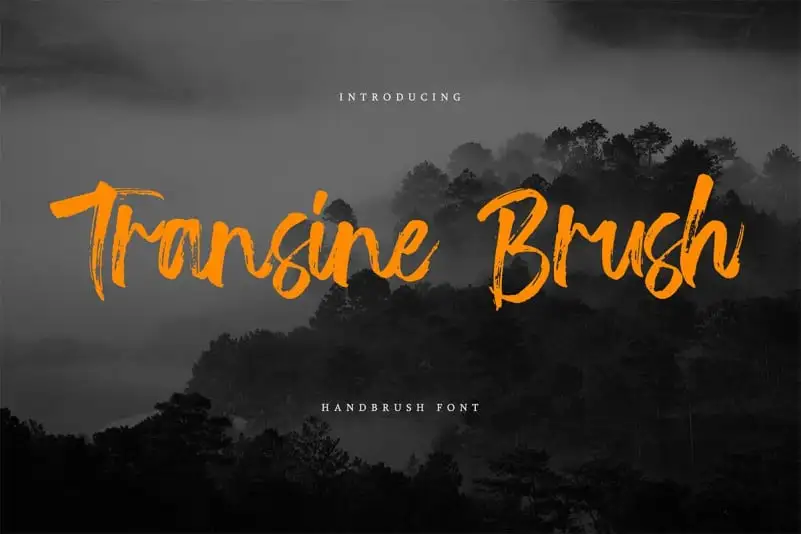
Transine Brush Font – Download Grátis
Introduzimos Transine Brush Font, uma elegante e moderna fonte feita com estilo casual. Criada pelo designer Vztype, Transine é perfeita para sua próxima criação visual como logotipos, cartões de presentes ou convites, caixas de embalagem, cabeçalhos, tipos de letra, letras finais, panfletos e até mesmo desenhos de roupas. Ideal tanto para projetos pessoais quanto corporativos, Transine Brush Font proporciona um acabamento casual e moderno sem perder a elegância necessária em sua tipografia. Descubra como esta font pode adicionar uma personalidade única a seus projetos gráficos.